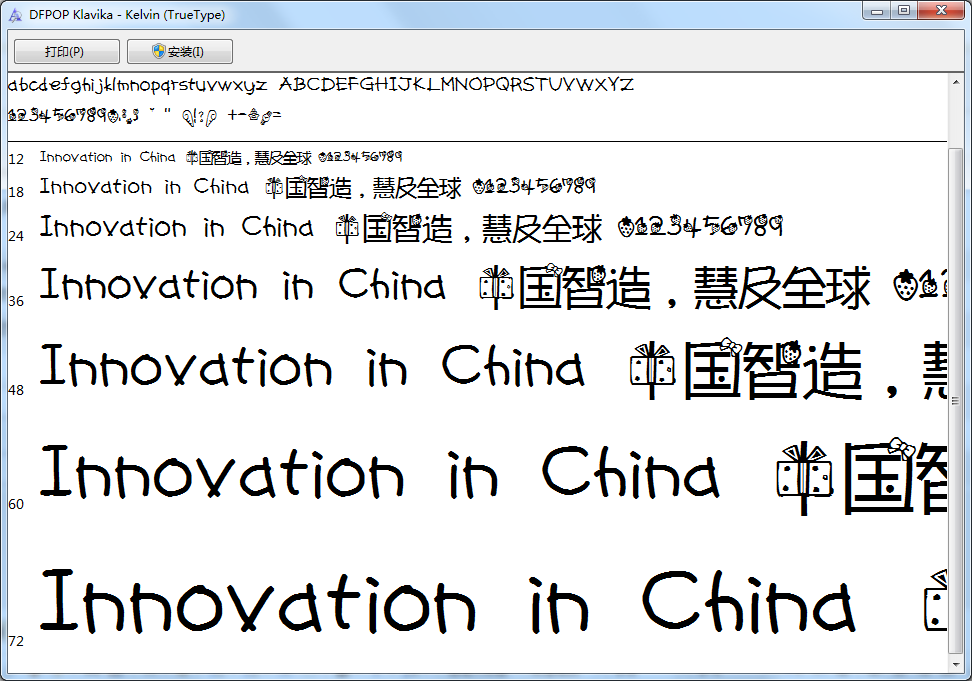
開心草莓優(yōu)字體是一款非??蓯鄣淖煮w軟件,有了它以后,你的字體本身有點(diǎn)圓圓的,非??蓯?,還有形象可口的草莓、漂亮可愛的蝴蝶結(jié)以及其他一些可愛的元素,喜愛的朋友趕快下載體驗(yàn)吧!
開心草莓優(yōu)字體是一款設(shè)計(jì)感很強(qiáng)的字體,它能夠?yàn)橛脩籼峁┲杏⑽碾p語字體,中文字體和數(shù)字設(shè)計(jì)起來都非??蓯?,有草莓、蝴蝶結(jié)裝飾。